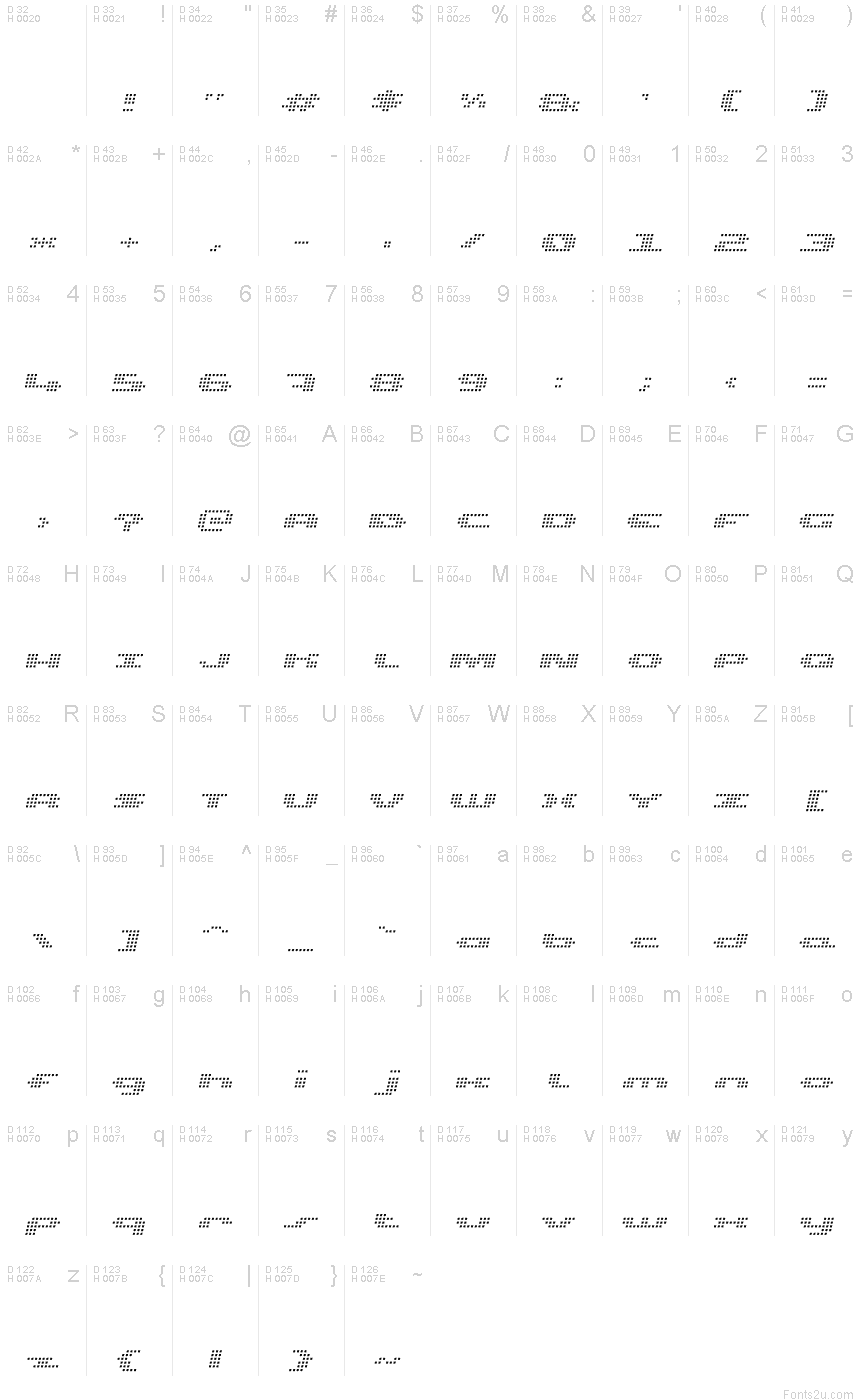
UP Tiny LCD Four 8 Light Italic هو خط عرض رقمي مجاني من UrbanPixel، يتميز بإيقاع حاد ومائل للأمام يحاكي شاشات LCD الصغيرة المكونة من نقاط مربعة دقيقة. تبدو الحروف بسيطة وميكانيكية، مع خطوط أفقية متقطعة وقطريات متدرجة وشبكة مدمجة تجعل التصميم يبدو وكأنه خرج للتو من شاشة جهاز محمول عام 2008.
هذا يجعله خياراً طبيعياً لشعارات الألعاب الكلاسيكية، وملصقات الـ Synth، والمنشورات التقنية، ونماذج الواجهات، والتصاميم التجارية القصيرة التي تتطلب خطاً مجانياً بنكهة أجهزة البكسل الحقيقية لضبط النغمة بسرعة. استخدمه لعناوين الأغلفة أو بطاقات العنوان أو رؤوس القوائم القصيرة، حيث يضفي هيكل مصفوفة النقاط المائل إحساساً سريعاً بالحركة حتى على الكلمات البسيطة.